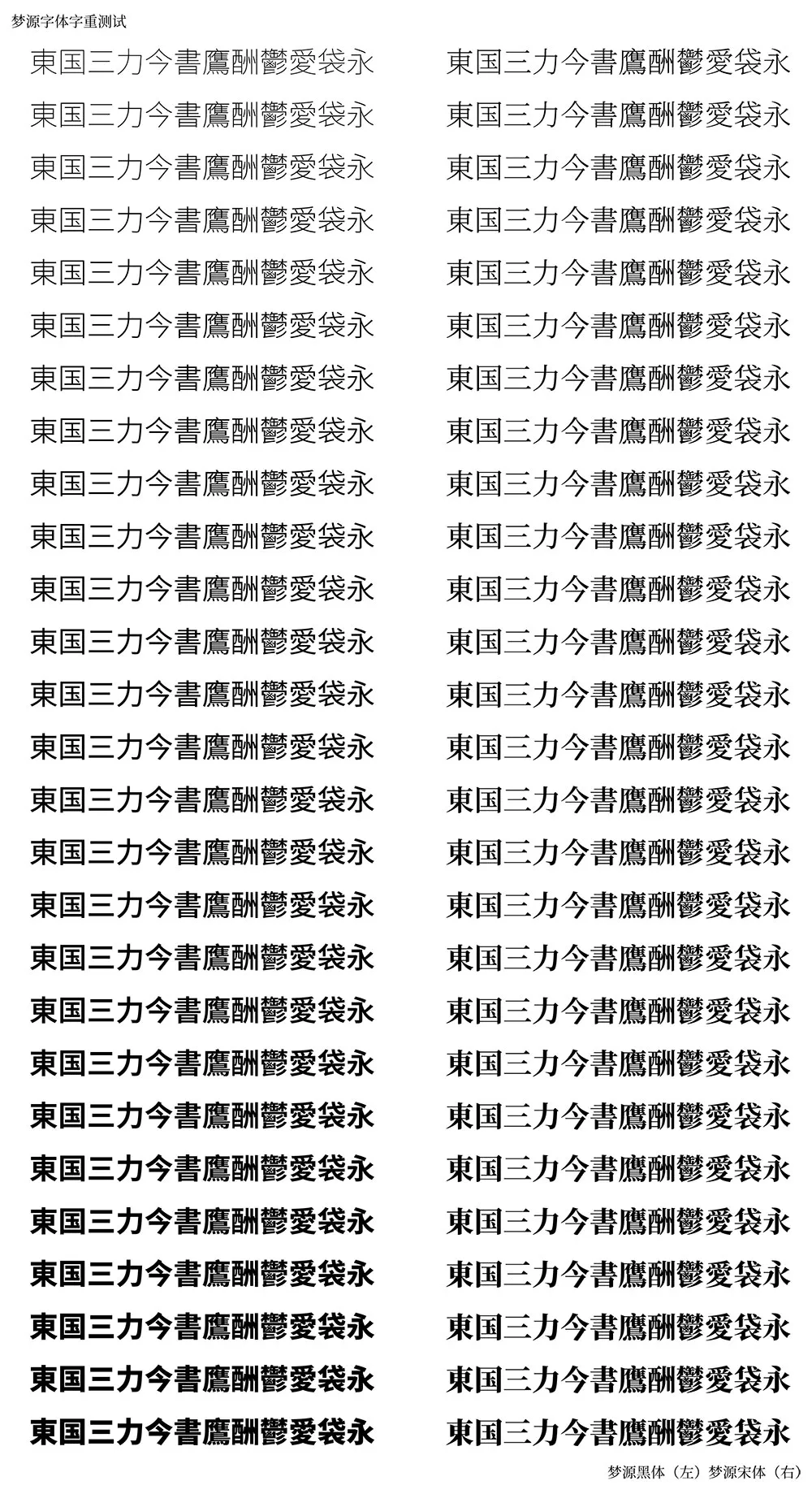
夢源黑體預覽
夢源黑體介紹
夢源黑體源自思源黑體多語言字體家族,兼顧字重、功能與兼容性,貨真價實的27字重!做設計起飛的趕腳!免費商用!絕非甚麼小作坊的描邊加粗!
可變版思源字體使精細的字重調節成為了可能。然而,可變字體因輪廓重疊、渲染故障、軟件兼容性等原因給實際使用造成了阻礙。本項目將可變版思源字體的大量中間字重實例化為傳統單字重字體,合併了重疊的曲線輪廓,在保證最大兼容性的前提下,提供更加細膩、豐富的字重選擇。此外,本項目修復了思源系列廣泛存在的 Adobe 行高過大問題。本系列字體的其他功能(如字形、豎排、kerning、多語言、異體字、曲線精度等)與思源系列保持完全一致,未做任何修改。
技術規格
樣式:W1 - W27 共計 27 字重
字符集:完整版含 6,5535 字符
異體字支持:簡、臺繁、港繁、日、韓
OpenType 功能(豎排支持等):完整收錄,與思源系列相同
Adobe 行高:標準行高,已修復思源系列存在的行高過大問題
Microsoft Office Style-Link:加粗按鈕 B 鏈接黑體的 W12 與 W22 字重,以及宋體的 W7 與 W20 字重
曲線格式:二次貝塞爾曲線
曲線精度(UPM, units per em):2048,即原版 OpenType/CFF 三次曲線的無損轉換
屏顯渲染策略:全字號亞像素抗鋸齒(Windows 10 及更新版本)
字重:本項目以可變版思源黑體和思源宋體為母版,對其字重軸 wght 進行插值運算,提取中間字重。插值算法經過了如下考量:
1、暴露給最終用戶的 wght 軸經 Adobe 添加的 avar 表人工干預,導致字重隨 wght 非線性增大(參見 issue #6)。插值算法需排除 avar 表的干擾;
2、加粗時,黑體和宋體的黑度變化不同:黑體的橫豎筆畫同時變粗,而宋體只有豎筆畫變粗,因此在人眼看來,黑體的加粗速度要高於宋體,且其細體字重比粗體對粗度的變化更為敏感。簡單的線性插值適用於宋體,但如果直接用在黑體上,就會導致細體字重被粗體“擠壓”。
插值算法:
1、繞開思源可變源文件中的 avar 表,確保插值算法不受人工預設值干擾;
2、夢源宋體採用線性插值(linear interpolation):從最細端 250 開始,粗度每步增加常數 25 ,直到最粗端 900,得到 250-275-300-...900 共計 27 字重;
3、夢源黑體採用二次多項式插值(quadratic interpolation):從最細端 250 開始,粗度每步增加 19.4 + f ^ 2;其中,係數 f 的起始值為 1,每一步增大 0.1;以此類推,直到最粗端 900,得到 250-270.4-291.01-...-900 共計 27 字重。
因為插值算法繞過了思源可變內置的 avar 表,所以本項目採用的 wght 值與思源可變字體沒有任何關聯,也沒有與思源在數值上完美對應的字重。在實際使用中,可對比思源字體找出夢源字體最接近的字重。
看起來就是加強版思源,為啥還要改名?
思源(Source)是 Adobe 的商業保留名稱,基於思源字體的修改及二次發佈不能使用這個名字。所以就用自己的網名起了這麼個名字,哈哈哈哈。